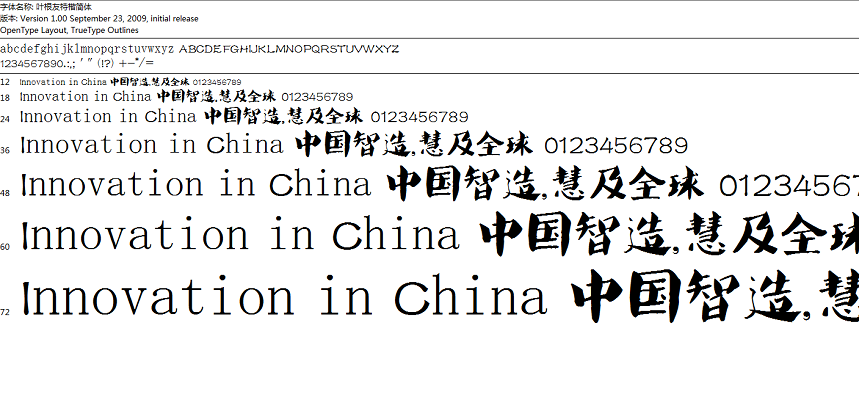
葉根友特楷簡體是一款極具特色的楷書字體,該字體剛勁有力,規(guī)正質(zhì)樸,是力與美的完美結(jié)合,給人一種威嚴(yán)肅穆的感覺,喜歡這款字體的朋友們快來綠色資源網(wǎng)下載體驗(yàn)吧!
葉根友特楷簡體是由葉根友開發(fā)設(shè)計(jì)的一套風(fēng)格獨(dú)特的楷書字體,區(qū)別于傳統(tǒng)書法楷書的中規(guī)中舉,在筆畫運(yùn)筆以及起筆等方面均有創(chuàng)新性的突破。筆法剛勁規(guī)正,風(fēng)格質(zhì)樸,有如刀鋒遒勁,結(jié)合了柳體、顏體、歐體的不同風(fēng)格而書寫的一套葉根友特楷體字庫。